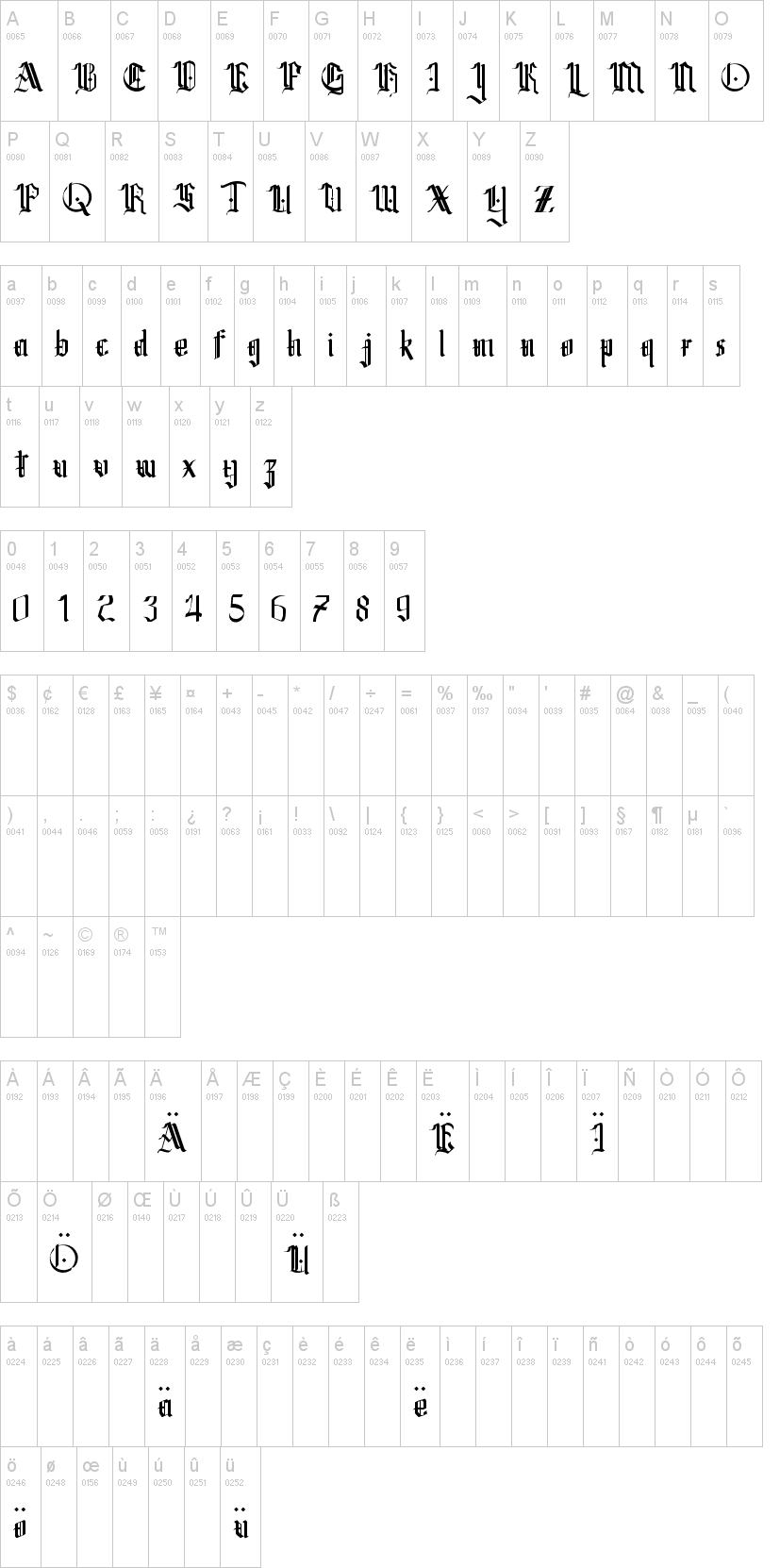
Omerta 字体是一种装饰性字体,它的设计灵感来自于黑手党文化。这种字体的特点是粗体、有力、鲜明,具有强烈的视觉冲击力。Omerta 字体的字母形状和线条都呈现出一种类似于手写的感觉,同时也融合了一些装饰性的元素,比如说线条的弯曲和扭转等,使其看起来更具有装饰性和艺术性。这种字体常被用于设计海报、标志、印刷品和其他需要引人注目的设计作品。内容介绍
Omerta是一款非常不错的手写艺术字体,具有很好的视觉感,适合于文化类的宣传设计、商业类品牌的广告和产品包装设计以及个性化文字排版等较多场景。